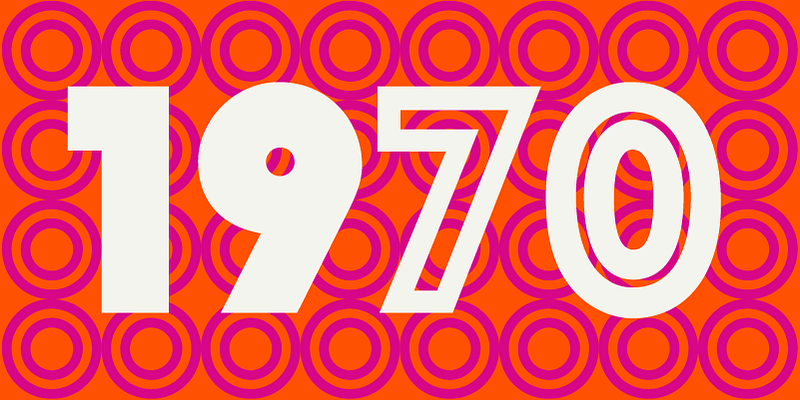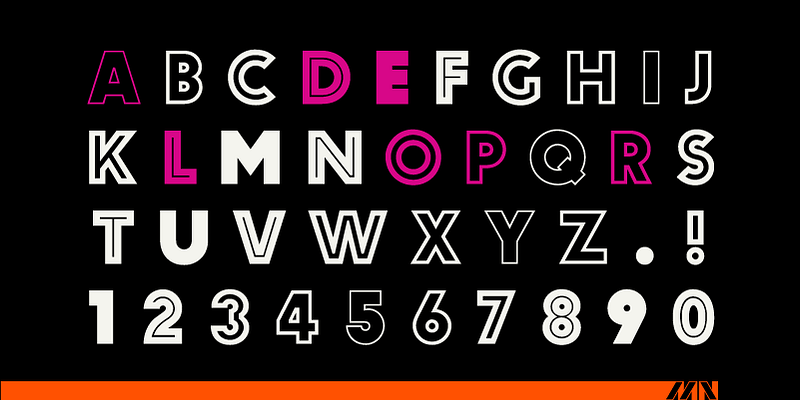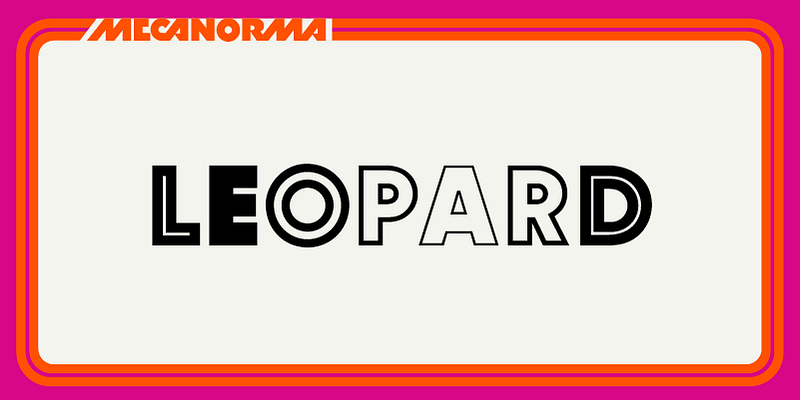
A empresa francesa Mecanorma foi uma das maiores fornecedoras mundiais de letras instantâneas para fricção. Em 1995, a Mecanorma se afastou do mercado gráfico profissional. Durante esse tempo, seus produtos de letras instantâneas para fricção foram fabricados pela Trip Productions BV. Em 2004, a International TypeFounders (ITF) licenciou as fontes digitais da Trip Productions BV e lançou o portfólio como Mecanorma Collection. Isso preservou uma das melhores bibliotecas de fontes digitais de fontes de exibição, combinando artes e ofícios reais nas ferramentas de hoje. Em 2014, a ITF firmou um acordo permanente com os sucessores da Trip Production. Este acordo confirmou os direitos digitais mundiais exclusivos da ITF para a coleção.